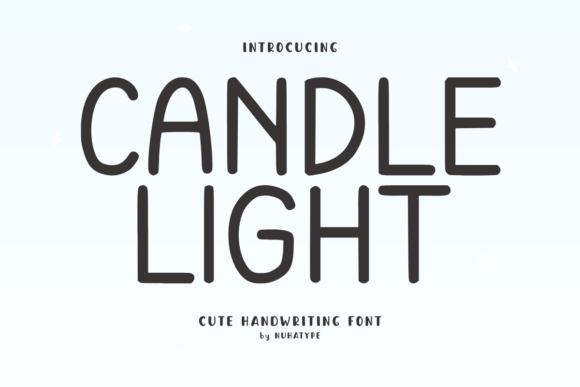
Candle Light
หากคุณกำลังมองหาเนื้อหาคุณภาพสูงเช่น Candle Light แพ็คเกจพรีเมียมนี้เป็นตัวเลือกที่ยอดเยี่ยมสำหรับโปรเจ็กต์สร้างสรรค์ของคุณ
สร้างขึ้นอย่างแม่นยำ Candle Light ให้เวกเตอร์ที่สะอาด พิมพ์ตัวอักษรที่ราบรื่น และใบอนุญาตเชิงพาณิชย์เพื่อความสบายใจ